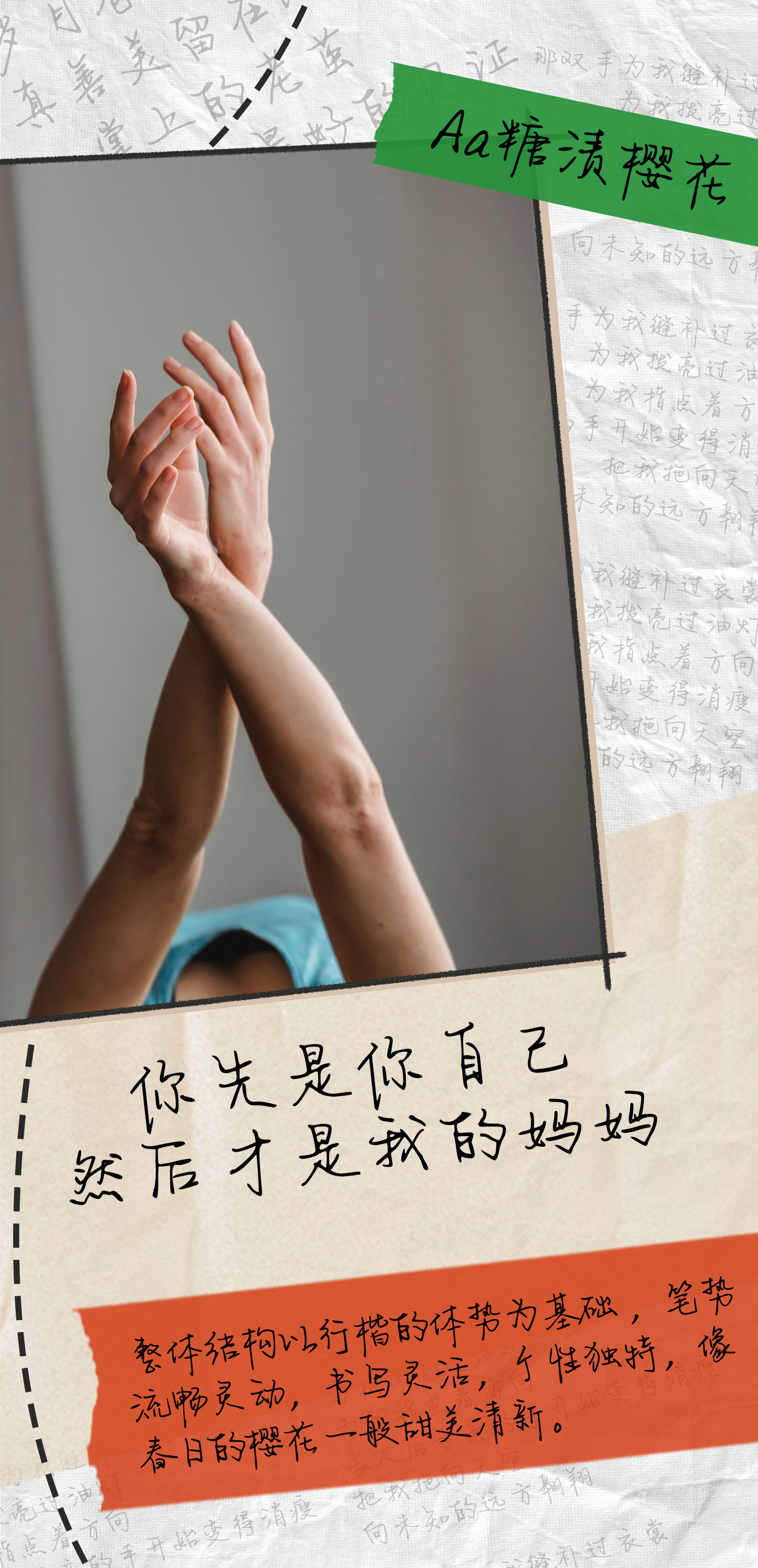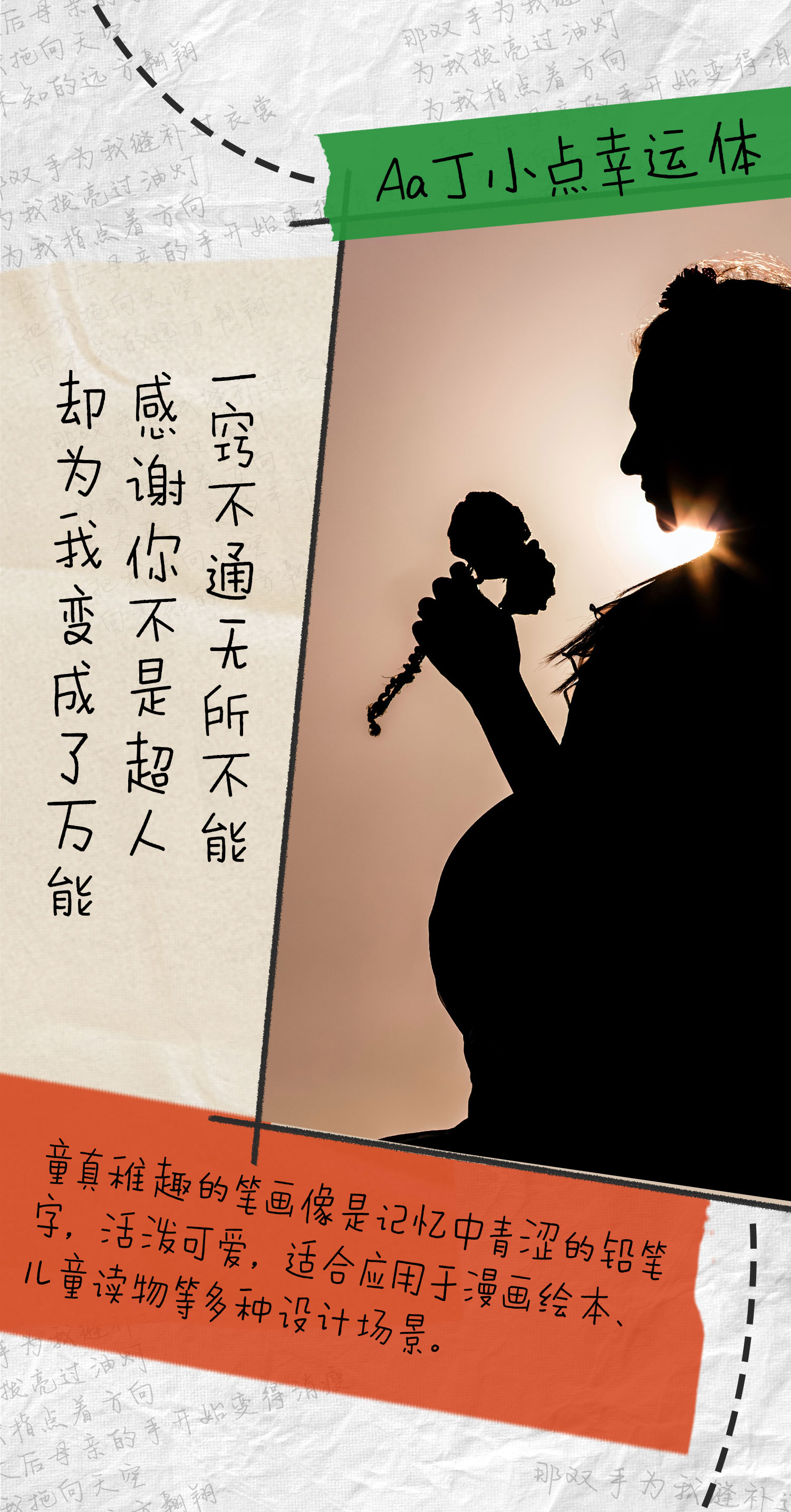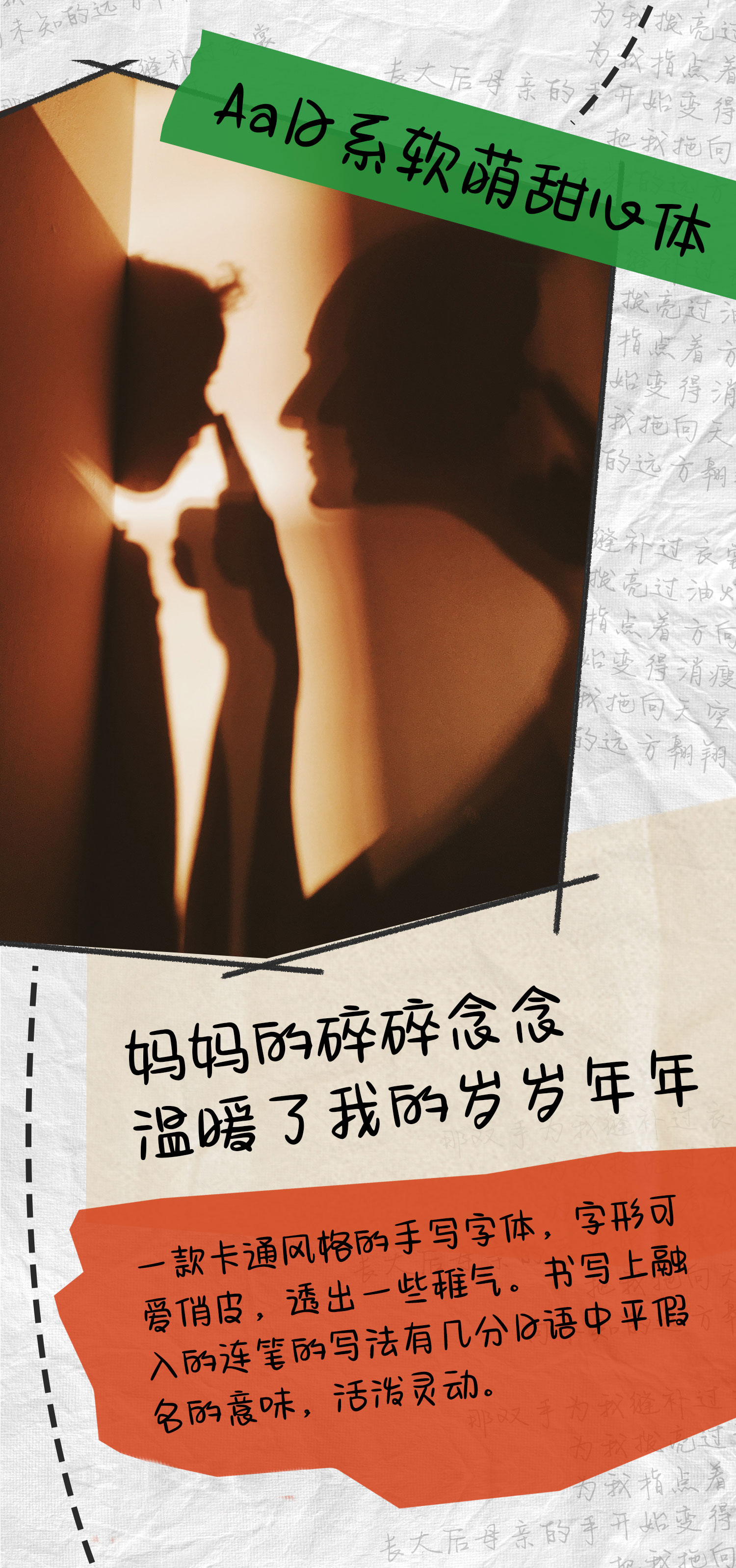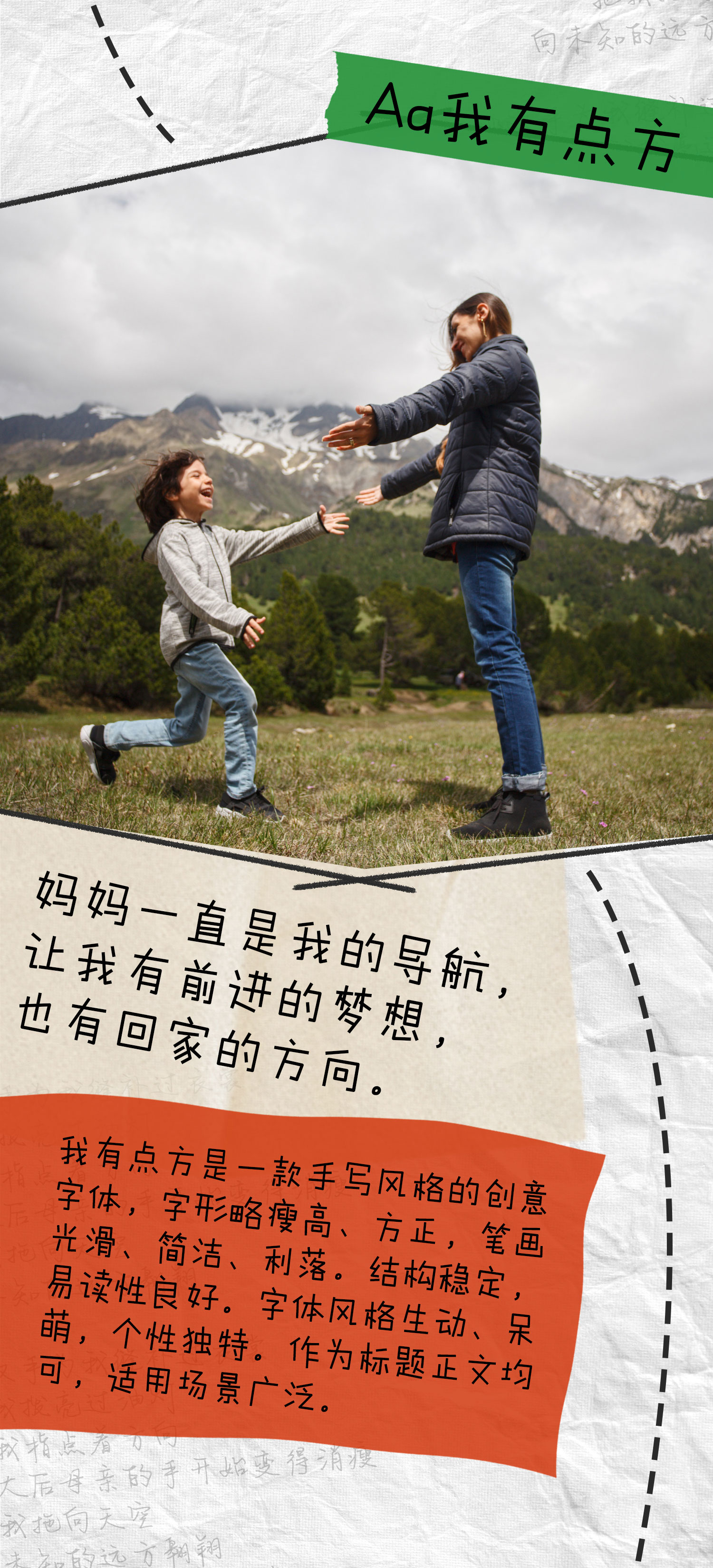
Aa字体推荐|母亲节,写给妈妈的爱
母亲节,写给妈妈的爱
Aa糖渍樱花
Aa丁小店幸运体
Aa日系软萌甜心体
一款卡通风格的手写字体,字形可爱俏皮,透出一些稚气。书写上融入的连笔的写法有几分日语中平假名的意味,活泼灵动。
Aa我有点方
我有点方是一款手写风格的创意字体,字形略瘦高、方正,笔画光滑、简洁、利落。结构稳定,易读性良好。字体风格生动、呆萌,个性独特。作为标题正文均可,适用场景广泛。